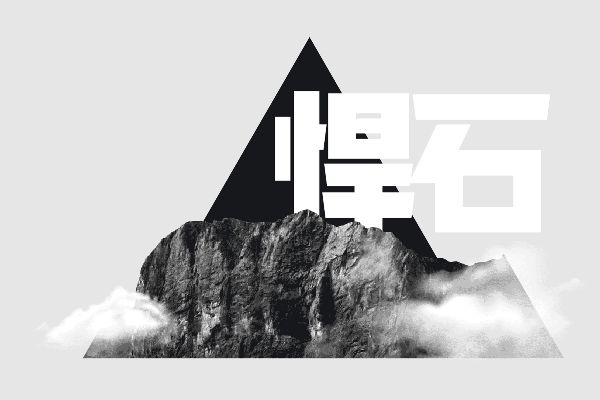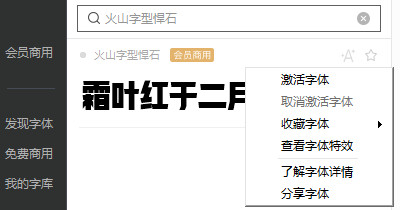
火山字型悍石是火山字型推出的艺术字体,这款字体笔触粗实,字形端正,给人以稳重的感觉,适合应用于艺术设计、各类广告和产品包装设计等领域。
火山字型,由一位从业多年的平面设计师创建,每套字体的风格设定皆来自日常设计需求中,从2016年开始成体系的制作中文字库,在2020年6月1日正式公开发行三套原创中文字型——眉月、悍石、修竹。